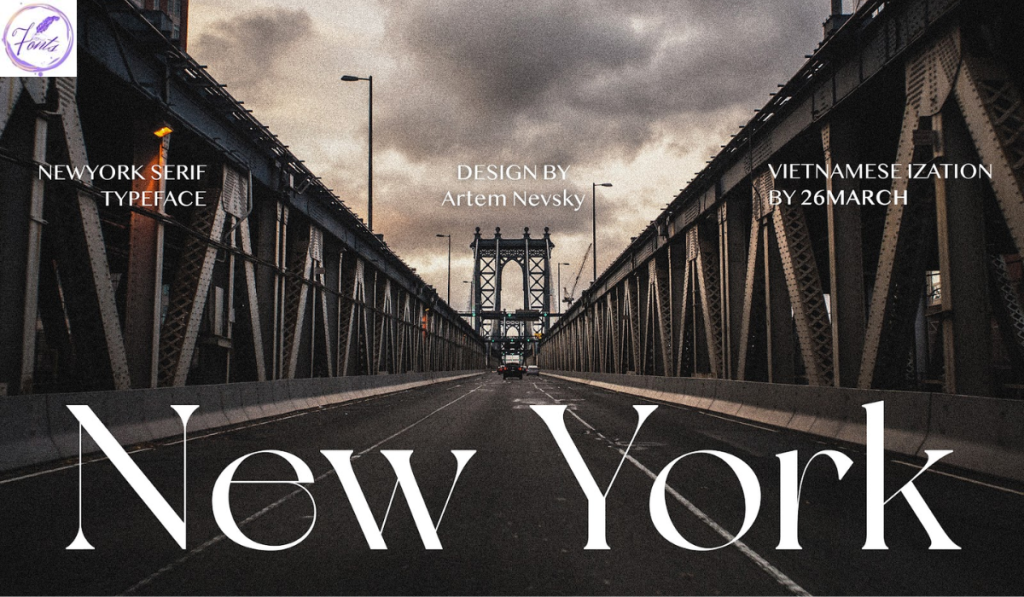
New York font việt hóa
Tác giả: Artem Nevsky
Ngày phát hành: 2016
Ngôn ngữ: Tiếng Việt, Tiếng Anh, và nhiều ngôn ngữ khác
Bộ Font: NewYork Typeface
Phân loại: cá tính, độc đáo, trang nhã, hiện đại
Kiểu chữ: serif
New york font là một font chữ serif đậm chất cổ điển và sang trọng, lấy cảm hứng từ phong cách typography của những tờ báo nổi tiếng ở New York vào đầu thế kỷ 20. Được thiết kế bởi nhà thiết kế tài ba Artem Nevsky và phát hành bởi Artem Nevsky vào năm 2016, new york font mang đến một hơi thở mới cho các thiết kế mang hơi hướng retro và vintage. Với sự kết hợp hài hòa giữa các nét chữ mảnh và đậm, cùng các chi tiết tinh tế và thanh lịch, new york font trở thành lựa chọn lý tưởng cho các dự án thiết kế như logo, bao bì sản phẩm, hay thiệp mời.
Đánh giá new york font
New york font sở hữu nhiều ưu điểm nổi bật. Bộ font bao gồm 6 kiểu chữ và hỗ trợ hơn 200 ngôn ngữ Latin mở rộng, mang đến sự linh hoạt và đa dạng trong việc sử dụng. New york font có khả năng hiển thị tuyệt vời trên cả màn hình lẫn in ấn, giúp các thiết kế của bạn luôn nổi bật và thu hút sự chú ý. Trong cuộc thi “Communication Arts Typography Competition 2019”, new york font đã vinh dự giành giải Bạc ở hạng mục “Typeface Design”. Font chữ này cũng nhanh chóng trở thành lựa chọn của nhiều thương hiệu nổi tiếng như Coca-Cola, Jack Daniel’s, và Levi’s trong các chiến dịch quảng cáo và thiết kế sản phẩm mang phong cách cổ điển.